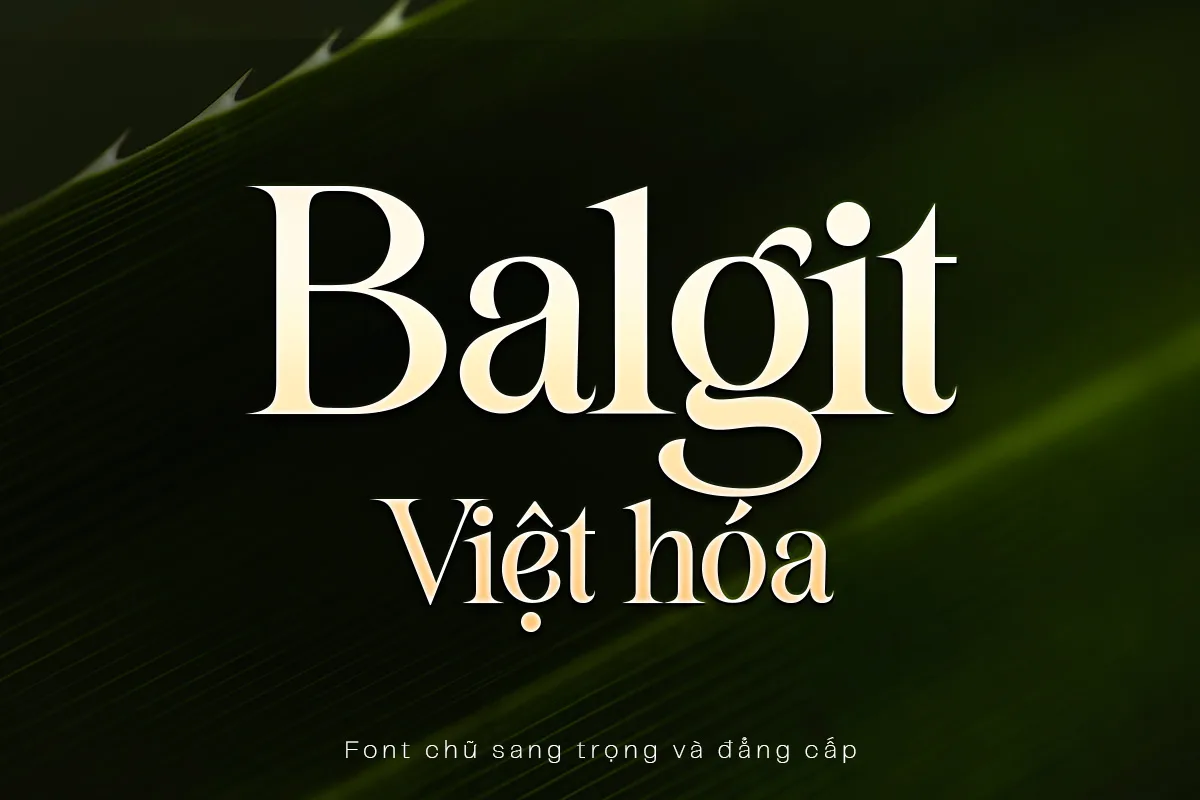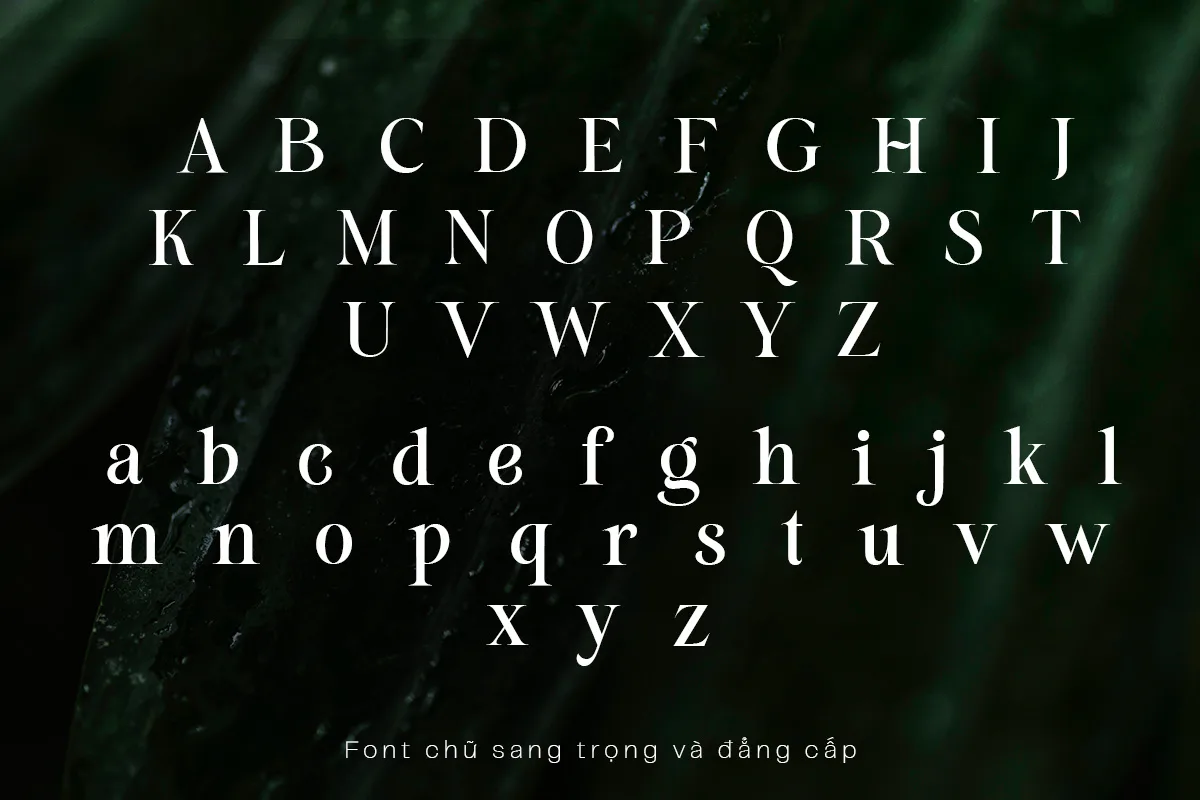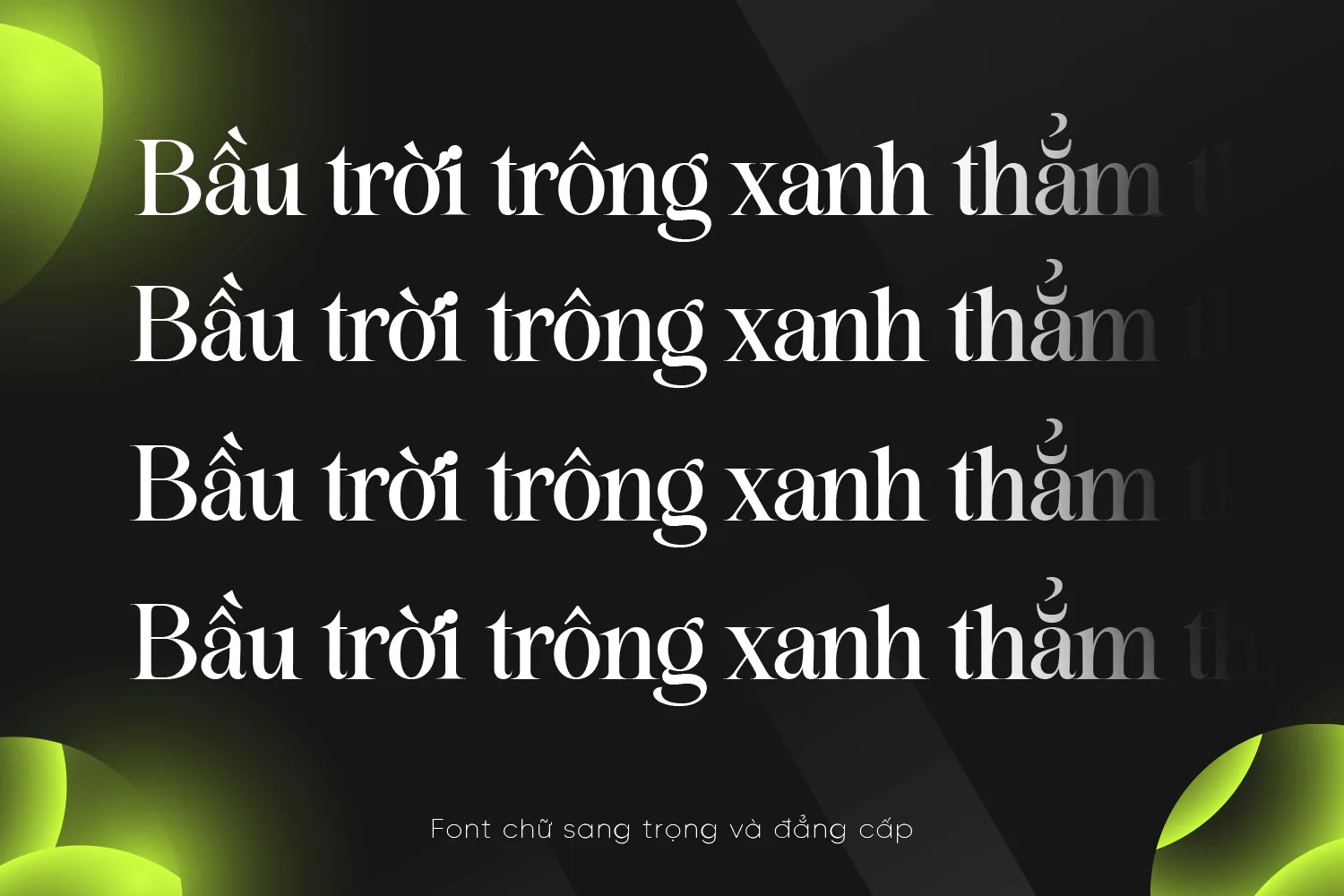
DVN Balgit – Font Việt hóa sang trọng, chuẩn mực cho thiết kế đẳng cấp
DVN Balgit Việt hóa là một kiểu chữ serif cao cấp mang đến vẻ đẹp cổ điển, sang trọng và tinh tế. Với cấu trúc chữ cân đối, đường nét thanh mảnh nhưng mạnh mẽ, font rất phù hợp cho các thiết kế thương hiệu cao cấp, bìa sách, thiệp cưới, poster thời trang hay tiêu đề tạp chí. Các ký tự được Việt hóa đầy đủ, chỉn chu với dấu tiếng Việt sắc nét, giúp bạn ứng dụng linh hoạt mà không mất đi tính thẩm mỹ. DVN Balgit là lựa chọn lý tưởng cho những ai theo đuổi sự tối giản nhưng vẫn giữ được khí chất thanh lịch và quyền uy.